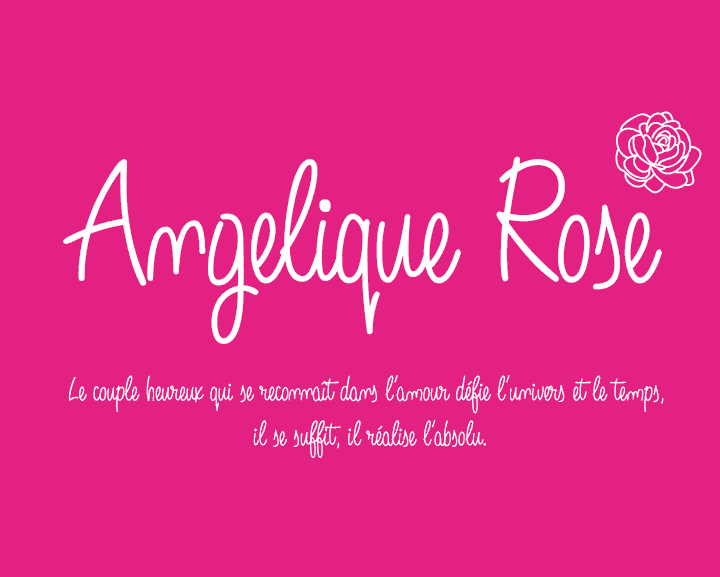
A Angelique Rose é uma fonte escrita a mão que foi desenhada meticulosamente com penes antes de ser digitalizada para uso nas máquinas dos computadores. Ela é perfeitamente adequada para projetos gráficos como painéis, cabeçalhos, convites de casamento ou qualquer texto onde haja uma contraste entre o estilo manual e outros fontes neutras, como sans-serif ou serif. A Angelique Rose oferece um visual único que combina a elegância das fendas do tipo serif com as nuances naturais da escrita a mão, criando um contrastão interessante em qualquer layout. Esta fonte é uma ótima escolha para quem busca algo especial e distintivo para seus projetos de design gráfico.